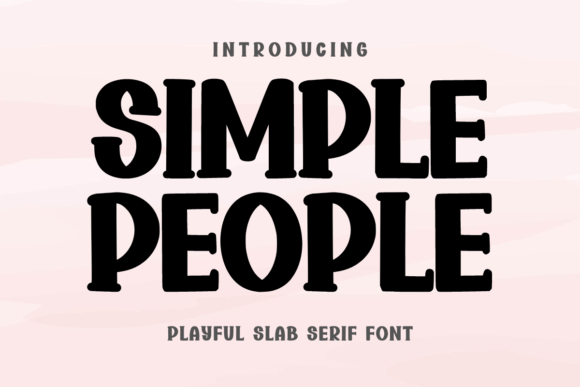
Simple People Font – خط عصري وأنيق بتصميم بسيط يجمع بين الحداثة والوضوح، مما يجعله مثاليًا للمشاريع الإبداعية. يتميز بتصميم نظيف وسهل القراءة، مما يجعله مناسبًا للعلامات التجارية، والتصميمات الرقمية، والمطبوعات، والعروض التقديمية، وحتى التصاميم الخاصة بمواقع الويب. أضف لمسة احترافية إلى أعمالك مع Simple People Font وامنح تصاميمك طابعًا فريدًا وجذابًا. ????✨